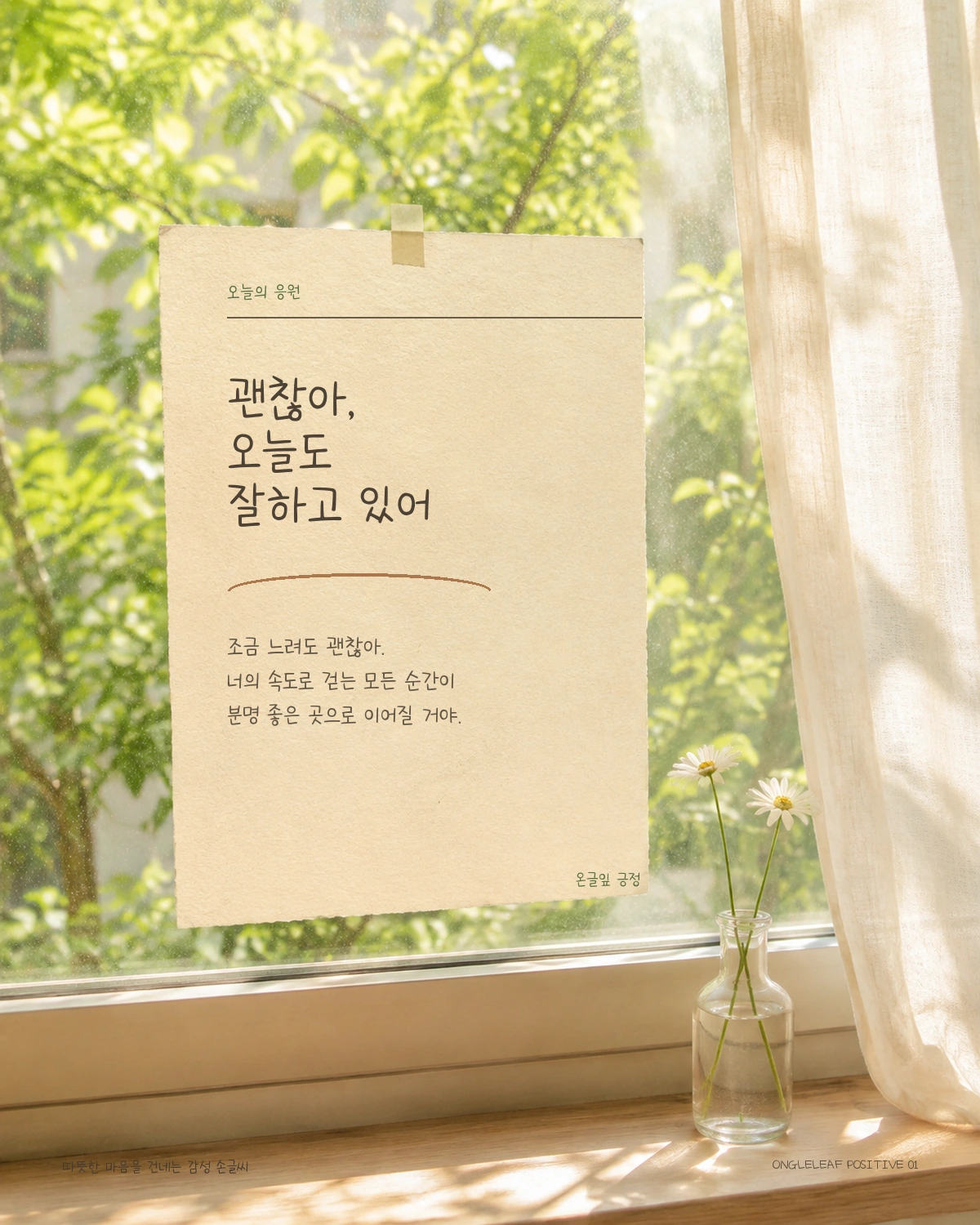
온글잎 긍정 — 온글잎에서 배포하는 무료 폰트입니다. 종이에 직접 쓴 글씨를 그대로 옮겨, 따뜻한 응원의 말투가 획에 그대로 묻어나는 손글씨체
보이저엑스가 운영하던 온글잎에서 2022년에 나온 손글씨 서체입니다. 온글잎은 종이에 쓴 손글씨를 찍어 올리면 인공지능이 나머지 글자를 채워 폰트로 만들어 주던 서비스로, 그래서 이 서체에는 글씨를 쓴 사람이 따로 있습니다. 다만 온글잎은 이니셜만 공개하는 방침이라 누구인지는 알 수 없고, 디자이너가 남긴 한마디에 인스타그램 계정이 적혀 있는 것이 전부입니다.
제작사가 쓴 조형 설명은 없어 형태는 파일을 보고 적습니다. 받침이 붙을 때 글자 높이가 눈에 띄게 달라지는 탈네모틀이라 손으로 쓴 리듬이 그대로 남아 있고, 낱자는 가로로 퍼져 있습니다. 획이 가늘어 자면을 채우는 비율이 낮으니 작은 크기나 복잡한 배경에서는 묻히기 쉽습니다.
굵기는 하나입니다. 온글잎 서체 중에서는 드물게 현대 한글 11,172자를 모두 담아 어떤 글자를 넣어도 빠지지 않습니다. 개인과 기업 모두 상업적으로 쓸 수 있고 임베딩과 BI, CI까지 허용되지만 **폰트를 수정하는 것은 금지됩니다.** 저작인격권을 보이저엑스가 갖고 있어서 계약이 아니라 저작권법 차원의 제약입니다. 그리고 온글잎 폰트 제작 서비스는 2023년 7월에 종료돼, 문의 창구가 이메일 하나뿐이라는 점도 알아 두시면 좋겠습니다.